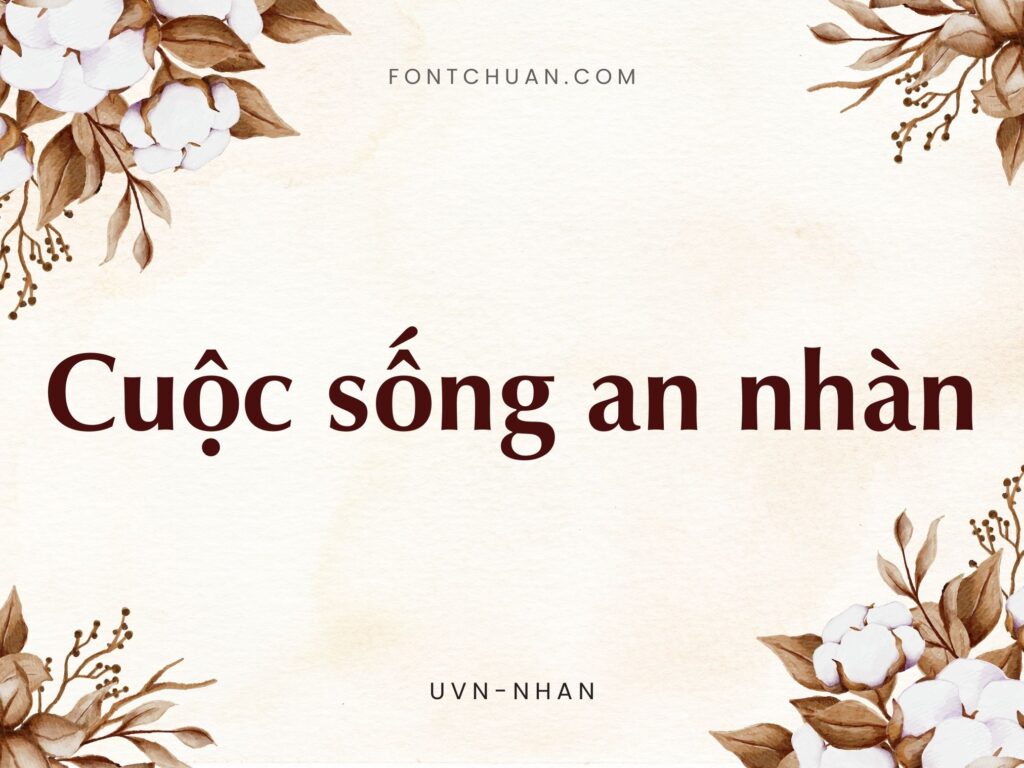
Font UVN Nhan Việt Hóa
UVN Nhân là một kiểu chữ serif thanh lịch, được thiết kế với các đường nét mềm mại và tinh tế, mang lại cảm giác trang nhã và chuyên nghiệp. Font này chỉ được sưu tầm và đăng bởi thành viên của Font Chuẩn.
UVN Nhân có cấu trúc chữ với các nét thanh mảnh và chân chữ rõ ràng, phù hợp cho các ứng dụng như thiết kế sách, báo, tạp chí và các ấn phẩm in ấn yêu cầu sự trang trọng và dễ đọc. Các ngành nghề như giáo dục, quảng cáo, công nghệ và bất động sản có thể tận dụng UVN Nhân để tạo điểm nhấn tinh tế trong thiết kế.